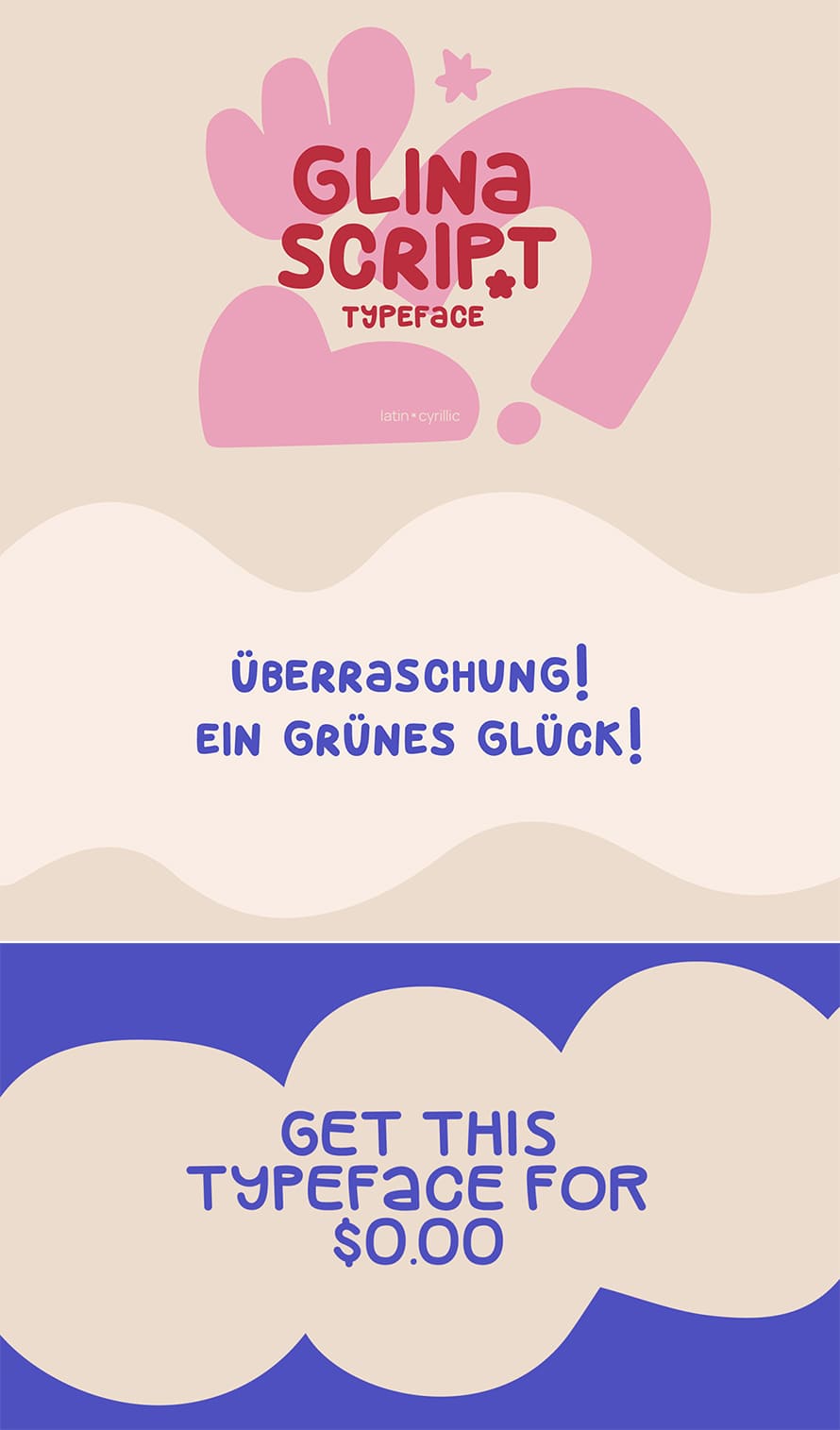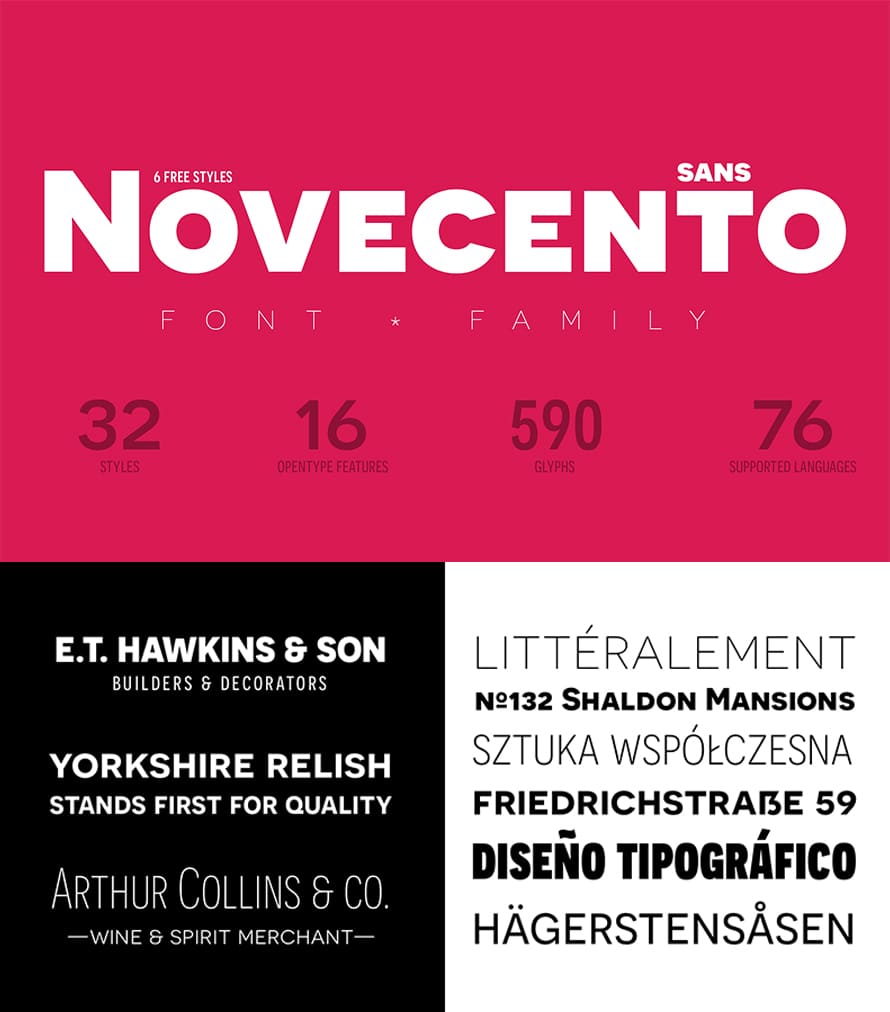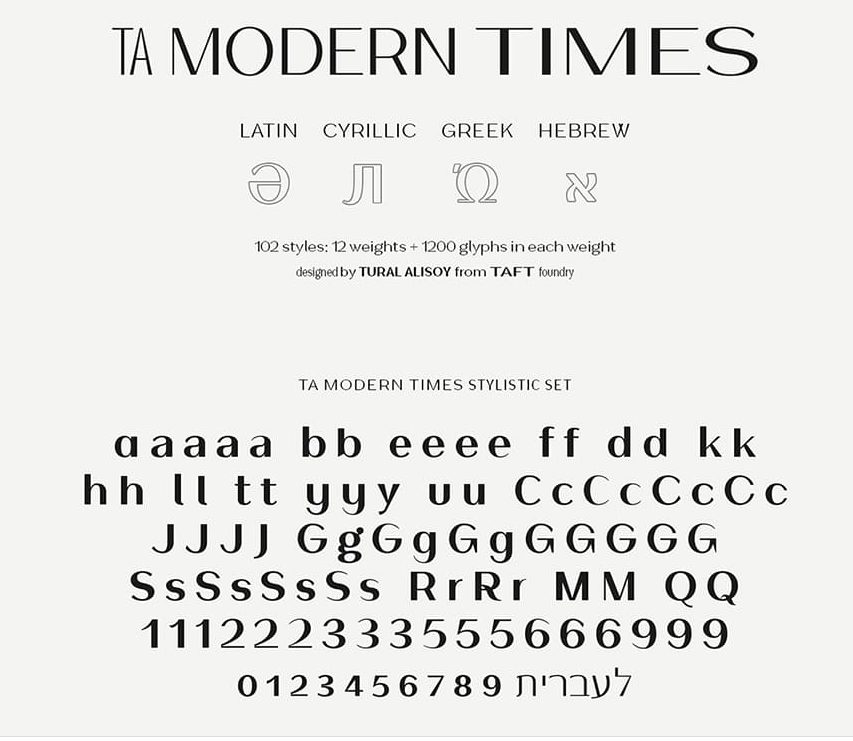
Wir alle wissen, dass Typografie das Rückgrat des Designs ist, und frische kostenlose Schriftarten sind Ihre Geheimwaffe für atemberaubende visuelle Gestaltung. Unter diesen ragen moderne Serifenschriften als zeitlose und doch zeitgemäße Wahl heraus, die Ihre Projekte sofort aufwerten können. Egal, ob Sie Logos, Websites oder Druckmaterialien gestalten, diese sorgfältig zusammengestellte Sammlung von neuen kostenlosen Schriftarten – inklusive stilvollen Serifen, Schreibschriften, schmalen Schriftarten und Vintage-Stilen – bietet endlose Möglichkeiten zum Experimentieren.
Typografie-Trends entwickeln sich ständig weiter, und wer mit den neuesten Stilen Schritt hält, sorgt dafür, dass seine Designs modern und ansprechend bleiben. Frische Schriftarten bringen neue Energie in Ihre Projekte und helfen Ihnen, sich in einer überfüllten digitalen Landschaft abzuheben. Mit dieser sorgfältig kuratierten Sammlung finden Sie einzigartige Schriftarten, die verschiedene Designbedürfnisse abdecken – von eleganter Branding bis hin zu auffälligen Überschriften.
Ta Modern Times Schriftart
Modern Times ist die beliebteste Schriftart, die von mir entwickelt wurde. Sie wurde häufiger verkauft als jede andere von mir erstellte Schrift. Die frühere Version unterstützte Westeuropa, Mittel-/Osteuropa, Baltikum, Türkisch, Rumänisch, Kyrillisch, Griechisch und Georgisch.
Ta Modern Times Schriftart
10 Pixel Schriftart
10 Pixel ist eine abgerundete Pixel-Schriftart mit drei einzigartigen Strichstärken: Light, Mild und Strong. Diese Schrift basiert auf einer 10-Pixel-Einheitshöhe, was ihr ein konsistentes und einheitliches Erscheinungsbild verleiht.
10 Pixel Schriftart
Ductile Display Kostenlose Schriftart
Ta Fabricans Kostenlose Schriftart
Die TA Fabricans-Schrift basiert auf der Film Fiction Semi Expanded-Schrift. Die Schrift unterstützt auch das hebräische Alphabet. Die Display-Version ist nur im lateinischen Alphabet verfügbar. Ich habe versucht, die Schrift sorgfältig vorzubereiten. Ich habe speziell nach dem hebräischen Alphabet gesucht und von meinen israelischen Kollegen profitiert.
Ta Fabricans Kostenlose Schriftart
Kiloy Rounded Techno Schriftart
Kiloy vermittelt den Eindruck ständiger Bewegung, mit abgerundeten, fließenden Linien, die an weiche Blasen erinnern und ein Gefühl sanfter Kinematik erzeugen. Spielerisches und Einfaches verbinden sich nahtlos zu einer sanften visuellen Präsenz. Die organische Fließfähigkeit der Schrift weckt Assoziationen mit futuristischem Design und verleiht ihr einen modernen, dynamischen Touch.
Kiloy Rounded Techno Schriftart
Glina Script Kostenlose Handschrift-Schriftart
Glina ist eine handgeschriebene Schriftart mit einem weichen, formbaren Charakter. Sie wurde für Latein und Kyrillisch in zwei Stilen entworfen und eignet sich am besten für Comics. Die Schriftart enthält auch Zahlen und einige Symbole.
Glina Script Kostenlose Handschrift-Schriftart
Geoform Kostenlose Schriftart
Geometrische Schriftarten sind eine Kategorie von Typografie, die sich durch ihre Abhängigkeit von geometrischen Formen wie Kreisen, Quadraten und Dreiecken auszeichnet. Diese Schriftarten betonen Klarheit und Struktur und führen oft zu einem modernen und sauberen Ästhetik, die Lesbarkeit und visuelle Anziehungskraft verbessert. Geometrische Schriftarten werden aus grundlegenden geometrischen Formen konstruiert.
Geoform Kostenlose Schriftart
Novecento Sans Kostenlose Schriftart